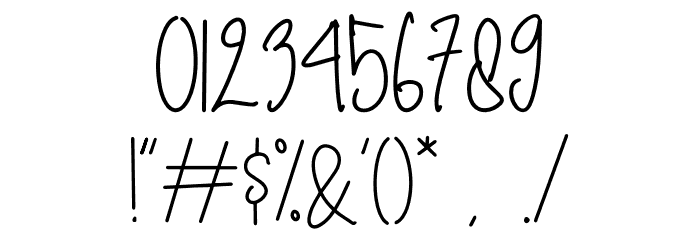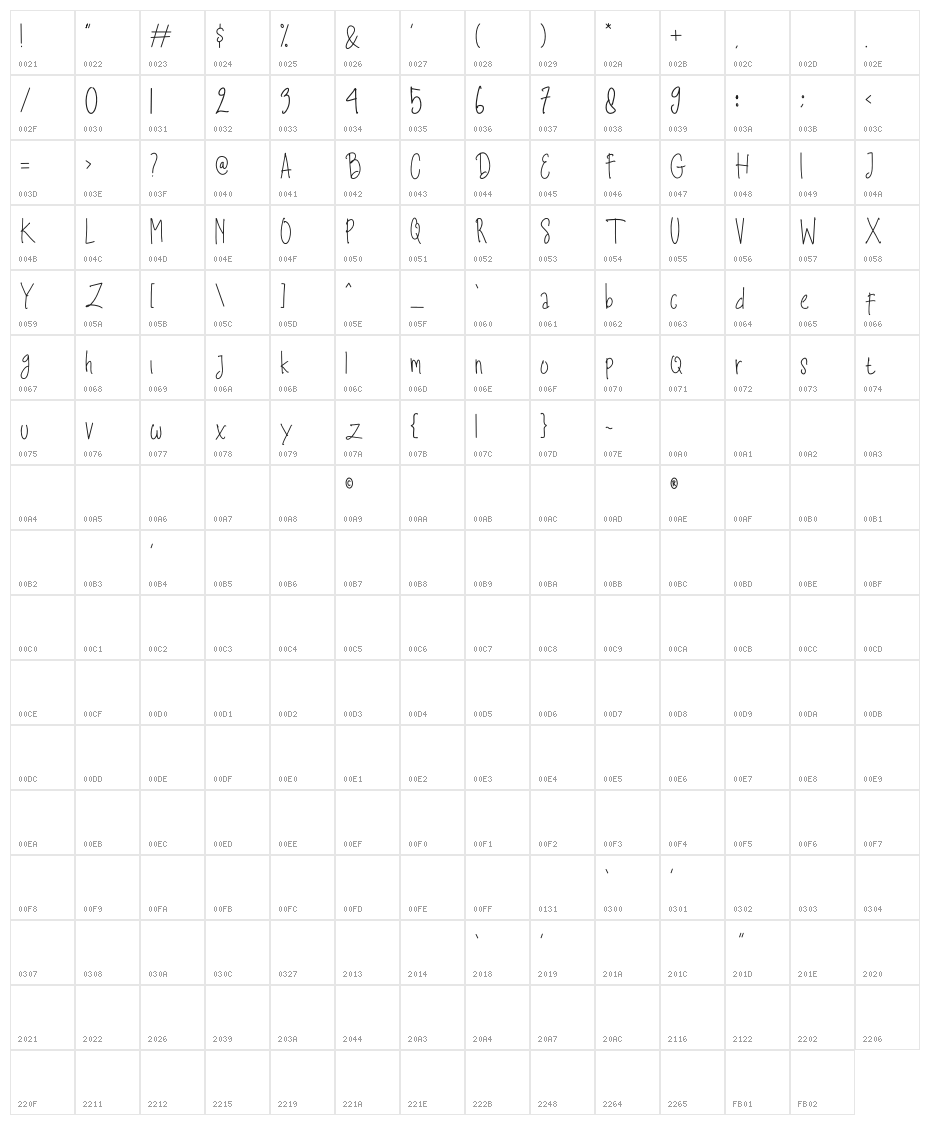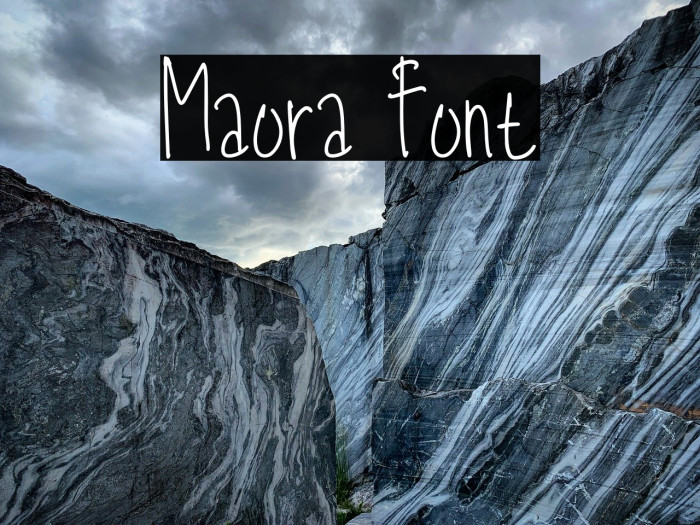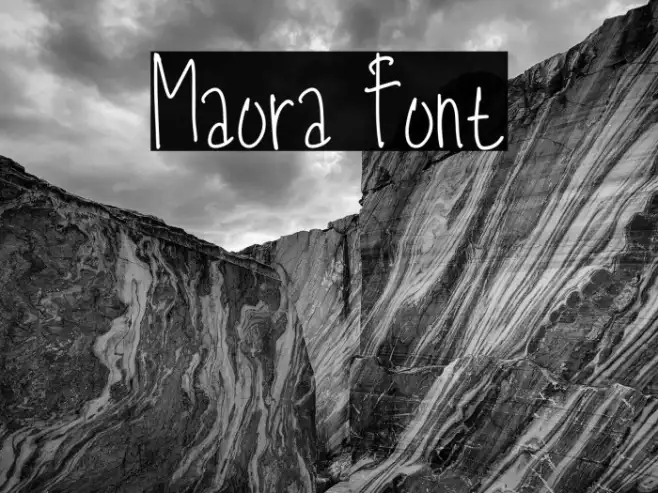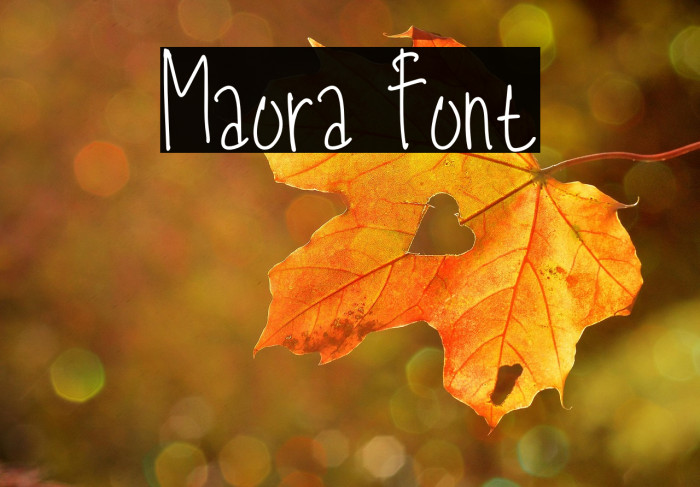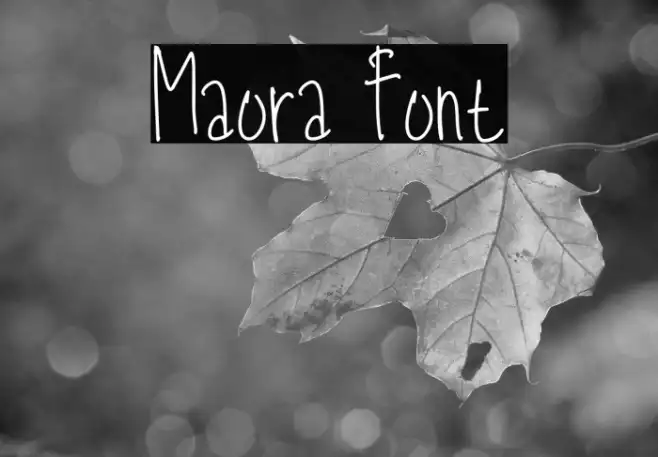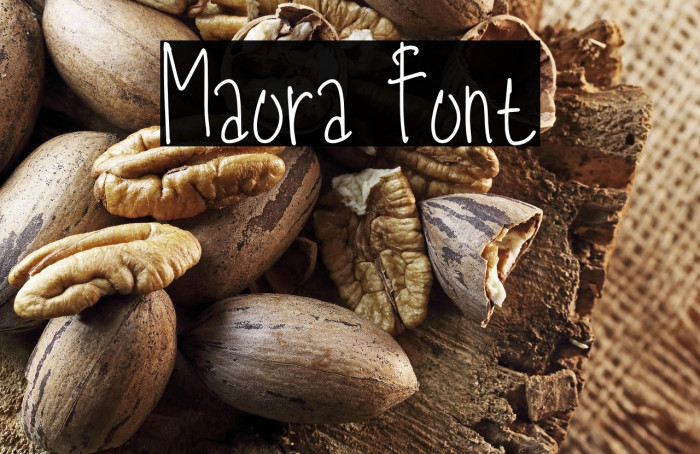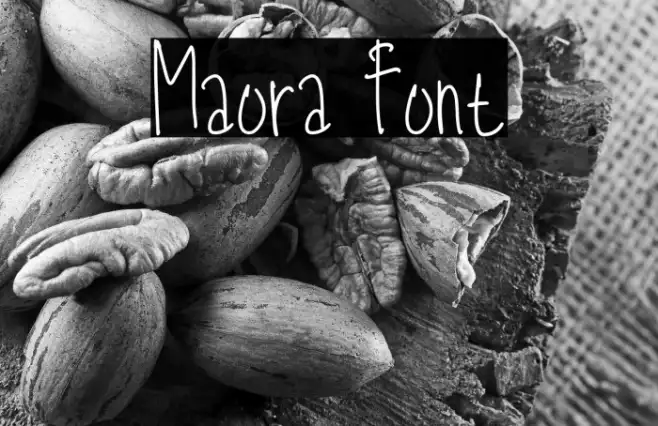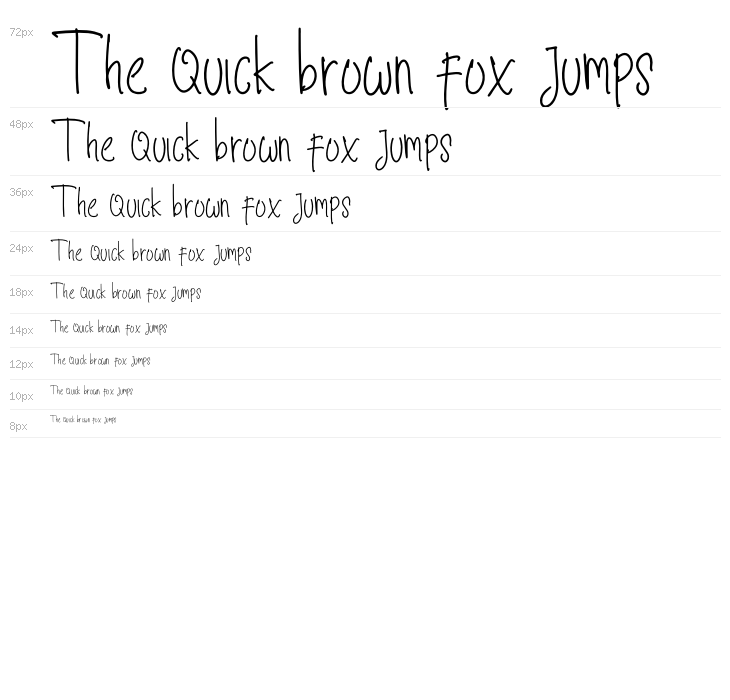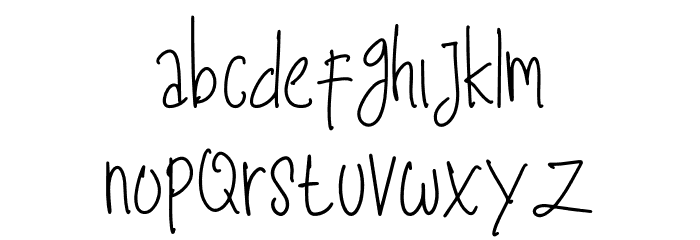
Maora Font
| Caso d'uso | Headlines, Logos, Informal Text |
| Progetti proposti | Ideal for greeting cards, children's books, playful branding, and social media graphics. |